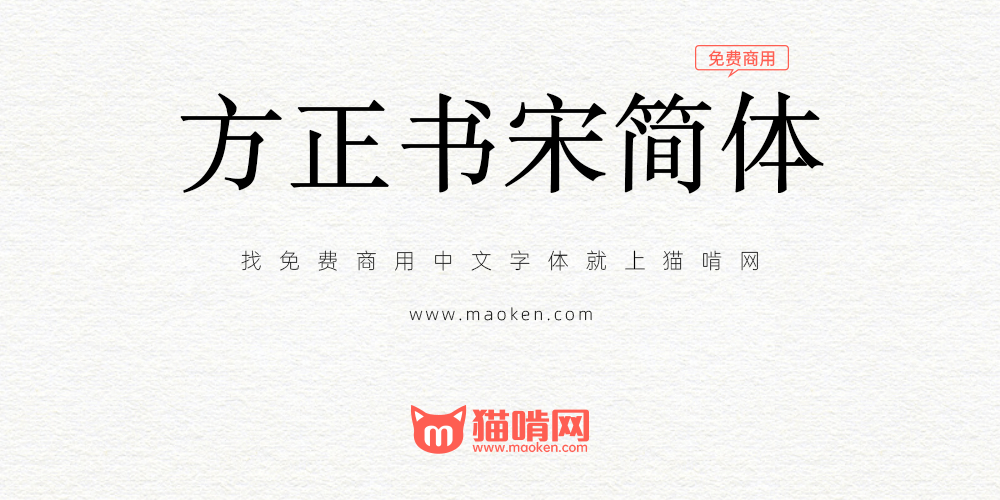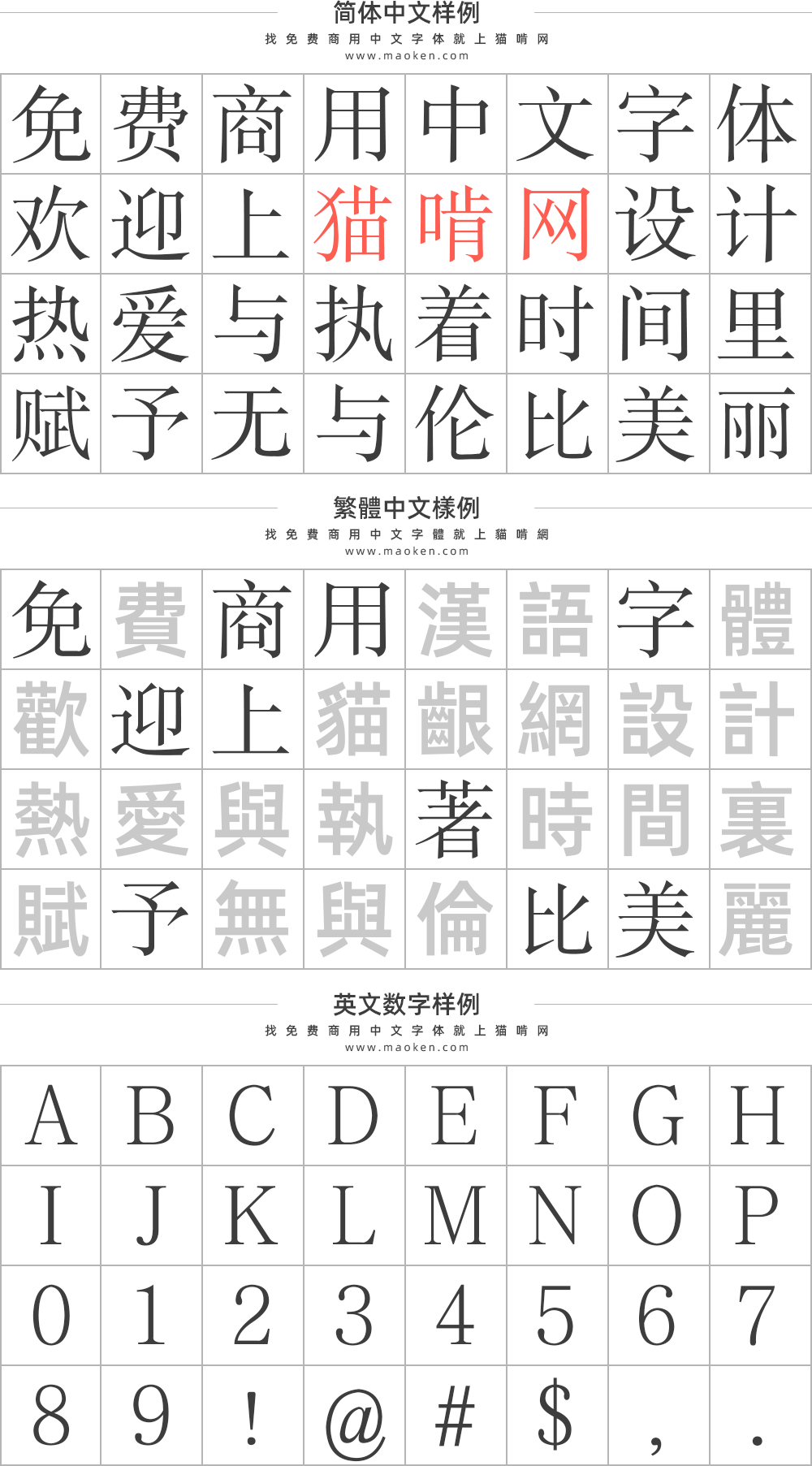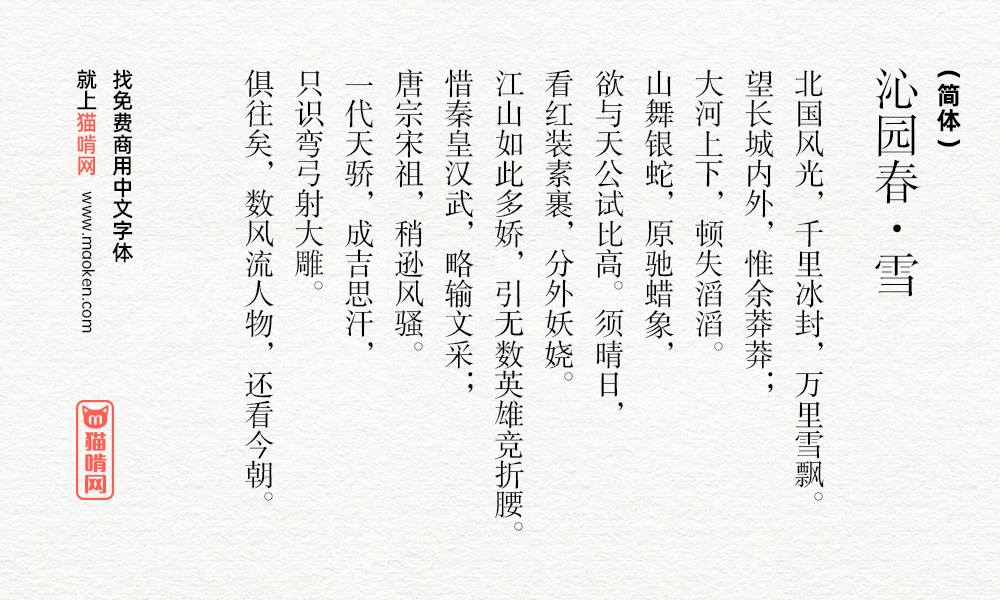
方正书宋简体:字形端正清秀中宫适度经典的正文宋体
说起方正字库,听到这个名号令各个设计师闻风丧胆。因为我们的第一印象是,糟了,是不是字体又侵权了?是不是又要被告了?但是,大家可能不知道,原来方正字库也有四款可以免费商用的字体,意不意外?惊不惊喜?这四款字体分别是「方正黑体」、「方正仿宋」、「方正楷体」、「方正书宋」。
「方正书宋」源自上海印刷技术研究所的宋二,原字形距今已有近60年。最初的设计就是专门针对最常用的小字号正文排版。方正书宋的字形端正清秀,中宫适度。凭着清晰爽目、久读不易疲劳、印刷适性好的优点,长期被作为杂志和书籍的正文首选字体,所以也是一款非常经典的正文宋体。